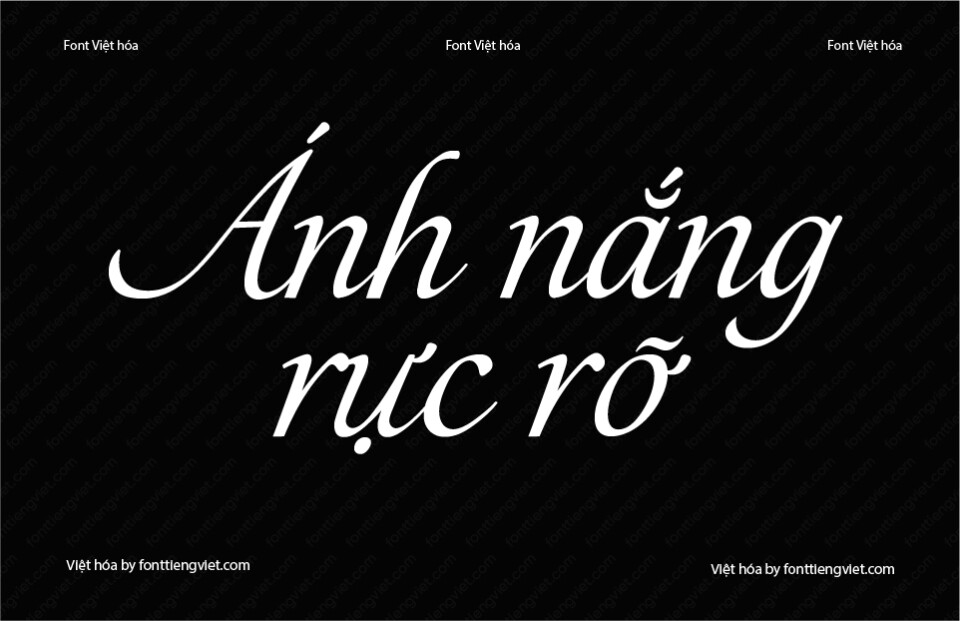
Trong thế giới thiết kế đồ họa ngày nay, việc lựa chọn một Font Chữ phù hợp có vai trò cực kỳ quan trọng, quyết định đến tính thẩm mỹ và thông điệp mà bạn muốn truyền tải. Đặc biệt đối với các bạn học sinh, sinh viên, giáo viên hay những nhà thiết kế trẻ tuổi đang chuẩn bị cho các đồ án, bài thuyết trình, hoặc các sự kiện quan trọng như kỳ thi tốt nghiệp, một bộ font chữ độc đáo và chuyên nghiệp có thể tạo nên sự khác biệt lớn. Và hôm nay, chúng ta sẽ cùng nhau khám phá một tuyệt phẩm đang gây sốt trong cộng đồng: Font Việt hóa 1FTV VIP Miracle History. Đây không chỉ là một bộ font thông thường, mà còn là nguồn cảm hứng bất tận cho những ai yêu thích sự kết hợp giữa nét cổ điển và hiện đại, mang đến vẻ đẹp lịch sử pha lẫn kỳ diệu.
Font Việt hóa 1FTV VIP Miracle History: Tuyệt Phẩm Của Sự Kết Hợp Lịch Sử Và Hiện Đại
Font Việt hóa 1FTV VIP Miracle History không chỉ đơn thuần là một cái tên dài mà còn là sự mô tả chính xác về những gì nó mang lại. Được thiết kế với cảm hứng từ những nét chữ cổ điển, thấm đượm hơi thở của lịch sử, nhưng lại được tinh chỉnh để phù hợp hoàn hảo với các ứng dụng hiện đại. Điều này làm cho nó trở thành lựa chọn lý tưởng cho nhiều dự án khác nhau, từ thiết kế logo, poster, thiệp mời, cho đến các ấn phẩm dành cho trường học và các bài thuyết trình ấn tượng. Sự “Việt hóa” hoàn chỉnh đảm bảo rằng mọi ký tự tiếng Việt đều được hiển thị một cách trọn vẹn và mượt mà, không gặp bất kỳ lỗi font nào, giúp người dùng tập trung hoàn toàn vào nội dung sáng tạo của mình.
Các bạn học sinh, sinh viên thường xuyên phải đối mặt với yêu cầu cao về mặt trình bày trong các bài tập lớn, khóa luận tốt nghiệp hay thậm chí là bài thi tốt nghiệp. Với Font Việt hóa 1FTV VIP Miracle History, việc tạo ra một ấn phẩm chuyên nghiệp, dễ đọc và thu hút ánh nhìn trở nên dễ dàng hơn bao giờ hết. Bộ font này giúp tạo điểm nhấn mạnh mẽ cho tiêu đề, trích dẫn, hoặc các phần quan trọng khác trong tài liệu, nâng cao chất lượng tổng thể của sản phẩm.
Ưu Điểm Nổi Bật Của Font Việt hóa 1FTV VIP Miracle History Trong Thiết Kế Giáo Dục
Một trong những ưu điểm lớn nhất của Font Việt hóa 1FTV VIP Miracle History là khả năng ứng dụng linh hoạt. Đối với ngành giáo dục, việc tạo ra các tài liệu học tập, giáo án, hoặc các thông báo sự kiện trường học cần sự rõ ràng, dễ đọc nhưng vẫn phải có tính thẩm mỹ. Bộ font này đáp ứng tốt cả hai tiêu chí đó. Với các nét chữ mạnh mẽ nhưng vẫn mềm mại, nó truyền tải sự trang trọng cần thiết cho các văn bản chính thức, đồng thời vẫn giữ được sự tinh tế, thu hút.
Giáo viên có thể sử dụng font này để thiết kế các bài giảng điện tử, phiếu bài tập, hoặc các chứng nhận khen thưởng cho học sinh, tạo nên sự khác biệt và chuyên nghiệp. Học sinh cấp 3, đặc biệt trong giai đoạn chuẩn bị cho các kỳ thi quan trọng như kỳ thi tốt nghiệp THPT, có thể dùng font này để làm bìa báo cáo, trang đầu của bài nghiên cứu khoa học, giúp bài làm của mình nổi bật và được đánh giá cao hơn về mặt hình thức.
Thêm vào đó, việc sử dụng font chữ độc đáo còn giúp kích thích sự sáng tạo ở người học. Thay vì chỉ sử dụng các font chữ mặc định quen thuộc, việc trải nghiệm và áp dụng các font mới như Font Việt hóa 1FTV VIP Miracle History mở ra một không gian mới cho tư duy thiết kế, khuyến khích các bạn trẻ khám phá và thể hiện cá tính riêng của mình thông qua các sản phẩm sáng tạo.
Ứng Dụng Đa Dạng Của Font Việt hóa 1FTV VIP Miracle History Cho Mọi Dự Án
Không chỉ dừng lại ở lĩnh vực giáo dục, Font Việt hóa 1FTV VIP Miracle History còn là một công cụ đắc lực cho các nhà thiết kế đồ họa chuyên nghiệp và bán chuyên. Từ việc tạo ra các ấn phẩm truyền thông, quảng cáo sản phẩm, cho đến thiết kế giao diện website hay ứng dụng di động, bộ font này đều thể hiện được sự độc đáo và khả năng thích nghi tuyệt vời. Với phong cách “Miracle History”, nó mang lại cảm giác vừa cổ điển, vừa hiện đại, rất phù hợp cho các thương hiệu muốn xây dựng hình ảnh sang trọng, có chiều sâu.
Các sự kiện đặc biệt như lễ kỷ niệm trường, buổi lễ tốt nghiệp, hay các cuộc thi học thuật cũng có thể tận dụng font này để thiết kế backdrop, banner, hoặc các ấn phẩm truyền thông, tạo nên một không khí trang trọng và đáng nhớ. Việc sở hữu một bộ font chất lượng cao và được Việt hóa hoàn chỉnh như Font Việt hóa 1FTV VIP Miracle History là một lợi thế lớn, giúp tiết kiệm thời gian và công sức trong quá trình thiết kế, đồng thời đảm bảo chất lượng đầu ra tốt nhất.
Đối với những ai đang tìm kiếm sự phá cách và muốn tạo điểm nhấn cho tác phẩm của mình, việc thử nghiệm với các biến thể và phong cách khác nhau của Font Việt hóa 1FTV VIP Miracle History sẽ mang lại những kết quả bất ngờ. Hãy để những nét chữ này kể câu chuyện của riêng bạn, truyền tải thông điệp một cách mạnh mẽ và đầy cảm xúc.
Tóm lại, Font Việt hóa 1FTV VIP Miracle History không chỉ là một bộ font chữ, mà là một nguồn cảm hứng dồi dào, mở ra cánh cửa cho sự sáng tạo không giới hạn. Dù bạn là một học sinh đang chuẩn bị cho kỳ thi tốt nghiệp, một giáo viên đang biên soạn tài liệu, hay một nhà thiết kế đang tìm kiếm sự độc đáo cho dự án của mình, bộ font này chắc chắn sẽ là một trợ thủ đắc lực. Với sự kết hợp tinh tế giữa vẻ đẹp lịch sử và sự linh hoạt hiện đại, cùng với khả năng Việt hóa hoàn hảo, Font Việt hóa 1FTV VIP Miracle History xứng đáng là một “kỳ tích” trong thế giới typography. Đừng ngần ngại khám phá và áp dụng nó để nâng tầm mọi ấn phẩm của bạn. Hãy trải nghiệm sự khác biệt mà một Font Chữ chất lượng cao có thể mang lại cho công việc và học tập của bạn.